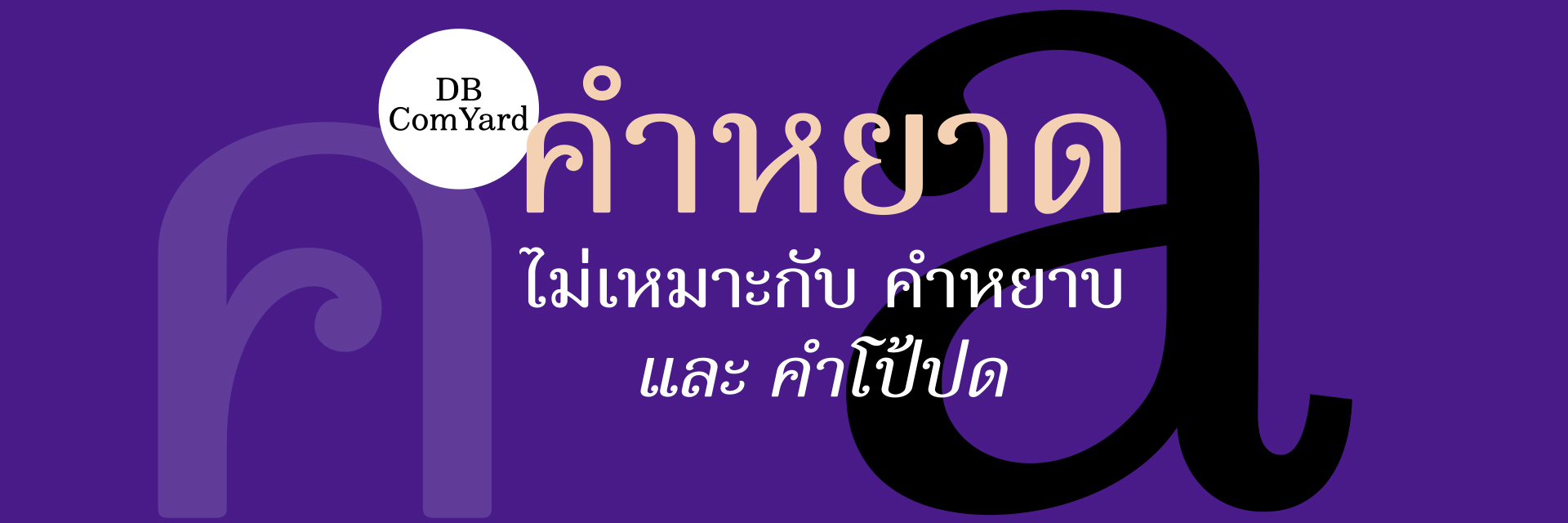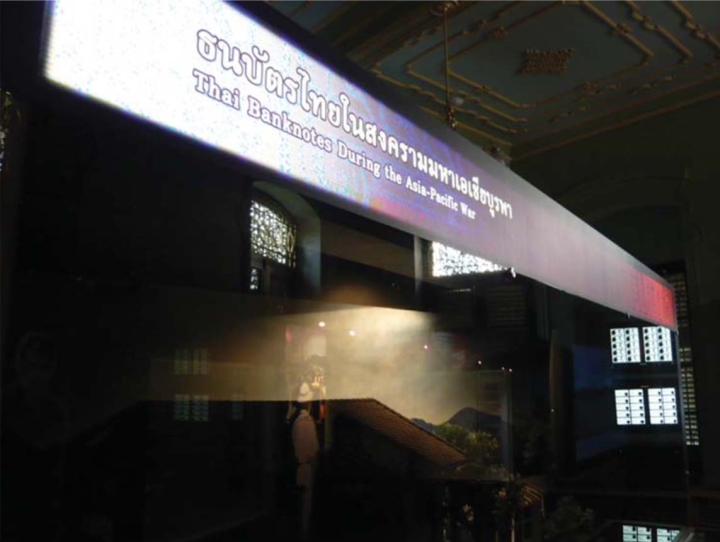
ตัวอักษรประดิษฐ์ของไทยแบบหนึ่ง ซึ่งแม้จะไม่มีหัวกลม แต่ก็ยังสามารถคงลักษณะจารีตประเพณีไว้ได้เป็นอย่างดี, คือ แบบตัวอักษรซึ่งมีหัวเปิด ขมวดปมกลมๆ ที่ส่วนปลายคล้ายยอดอ่อนของใบเฟิร์น, ลักษณะที่ว่านี้สามารถพบเห็นในแบบ ตัวพิมพ์ Clarendon ที่ออกแบบโดย Robert Besley ตั้งแต่ปี ค.ศ.1845 ปรากฏให้เห็นในตัวพิมพ์เล็ก (Lower Case) หลายตัว เรียกว่า "circular terminal". จุดเด่นของตัวอักษรไทยสไตล์นี้อีกประการหนึ่งคือ ส่วนปลายหางอักษรจะมีลักษณะเส้นหนักเบาตวัดปลายคล้าย stroke ที่เกิดจากปลายพู่กันอย่างจีน เราจะเห็นแบบอักษรกลุ่มนี้กระจายอยู่ทั่วประเทศ ตามป้ายร้านค้าเก่าที่ยังอนุรักษ์ไว้, ป้ายโรงเรียน สถานที่ราชการ, วัด, วัง ฯลฯ ด้วยระดับความละเอียดประณีตบรรจงแตกต่างกันออกไปตามระดับฝีมือช่าง, บ้างก็เป็นงานเขียนด้วยสี, บ้างก็เป็นตัวอักษรไม้หรืองานปูนปั้น ฯลฯ
ลักษณะรูปลักษณ์อักษรที่ดูอ่อนช้อยเป็นไทย ดังที่ผมได้กล่าวไปแล้วนั้น เป็นไปได้ว่าเกิดจากการคลี่คลายลายเส้นในงานจิตรกรรมไทยของช่างเขียน ช่างสลัก ช่างปูนปั้นของไทยเอง หรืออาจเป็นการซึมซับปรับปรุงมาจากต่างชาติ (ส่วนหัวมาจากทางยุโรป อเมริกา และส่วนหางมาจากจีน) ก็เป็นไปได้
ถ้าลองย้อนศึกษาดูสิ่งพิมพ์โฆษณาไทยในช่วงปี พ.ศ. 2470-2479 จะพบลักษณะที่ว่านี้ในตัวอักษรที่เขียนด้วยมือเพื่อนําไปทําบล็อคพิมพ์. ตัวเรียงพิมพ์ตะกั่วที่ใช้พิมพ์ในยุคนั้นคงมีเพียงแบบเดียวที่มีลักษณะหัวคล้าย circular terminal คือ "โป้งแซ" ตัวพาดหัวยอดนิยมที่ได้รับการยอมรับว่างดงามที่สุดของยุคตัวเรียงตะกั่ว, อย่างไรก็ตามนับจากโป้งแซเป็นต้นมา ก็ยังไม่มีตัวพิมพ์ยุค phototype setting (ที่คนไทยนิยมเรียกตัวคอมพิว) หรือแม้แต่เป็นแผ่นอักษรลอกที่มีลักษณะหัวอย่างโป้งแซออกมาให้เห็นเลย. เมื่อ PSL Thai Common ฟอนต์ PostScript ของ พัลลภ ทองสุข ออกสู่ตลาดจึงสามารถเติมเต็มช่องว่างที่ขาดไปได้อย่างดี, ลักษณะสําคัญของ PSL Thai Common คือรูปทรงที่ค่อนข้างผอมประหยัดที่ในการใช้พาดหัว, สัดส่วนแบบง่ายๆ คือ รูปอักษรพยัญชนะส่วนใหญ่ที่ดูกว้างใกล้เคียงกัน ประกอบกับรายละเอียดอื่นๆ เช่น เส้นคอของอักษร ค, ต ที่เหยียดตรง ทําให้ชื่อ Thai Common ฟังดูเหมาะสมเพราะรูปลักษณ์ดูเป็นไทยๆ ธรรมดาดี ค่อนไปทาง "ชาวบ้าน" มากกว่า "ชาววัง"
ฟอนต์ไทยกึ่งพาดหัวกึ่งตัวเนื้อ ย้อนยุคกลับไปหาคุณค่าในอดีตด้วยการเพิ่ม "จริต" เข้าไปในรูปอักษร
เพื่อบอกกล่าวอย่างเป็นทางการ เกิดจากการนำ DB ComYard มาปรับปุงส่วนหัว, หาง และสัดส่วนอักษรให้แคบลง
ปัญหามันอยู่ที่ว่า ในโลกยุค Branding ที่ต้องสร้างคุณค่าผ่านตัวพิมพ์นั้น อย่าว่าแต่สินค้าหรือธุรกิจบริการชั้นสูงที่เน้นความเป็นไทยเลย แม้แต่ร้านอาหารไทยเล็กๆ หรือสินค้า SMEs ที่อยากดูดีกว่า OTOP แบบพื้นๆ ก็ยังมีความต้องการยกระดับภาพลักษณ์เช่นเดียวกัน, PSL Thai Common ซึ่งตั้งใจเกิดมาเป็นชาวบ้านจึงไม่อาจรองรับความต้องการได้ครบ. ยิ่งถ้าเป็นงานที่ใช้สื่อถึงงานศิลปะชั้นสูง หรือถวายงานเจ้านายชั้นสูงแล้ว ตัวพิมพ์ยิ่งต้องเพิ่มความประณีตวิจิตรบรรจงเข้าไป เพื่อให้ได้บุคลิกสอดคล้องกับเรื่องราวที่นําเสนอ. กล่าวอย่างเป็นธรรม ไม่มีแบบฟอนต์ใดในโลกที่ใช้ได้ครอบจักรวาล, ดีบี คําหยาด จึงถือกําเนิดขึ้นเพื่อเป็นการช่วยเติมเต็มช่องว่างที่ขาดหายไปให้สมบูรณ์ยิ่งขึ้นไปอีก
การกําหนดสัดส่วนโดยรวมของตัวพิมพ์ "คําหยาด" ชุดนี้ ผมตั้งเป้าให้ใกล้เคียงกับแบบตัวพิมพ์เนื้อความมาตรฐานของไทยให้มากที่สุด ทั้งนี้เพื่อให้สามารถใช้เป็นตัวหัวข้อรอง (subhead) หรือตัวโปรยให้อ่านยาวๆ ได้ง่าย โดยไม่ต้องนํา PSL Thai Common มาสั่งเพิ่มความกว้างเหมือนที่เคยนิยมทํากันมา) หรือแม้แต่ใช้พิมพ์ร่วมเป็นส่วนหนึ่งในเนื้อความได้โดยที่ยังดูกลมกลืนไม่แปลกแยกจากกัน. รายละเอียดส่วนใหญ่ในเส้นร่างของผมเป็นการประสมเล็กประสมน้อย จากสิ่งประทับใจที่ซึมซับมาจากงานโฆษณาเก่าๆ, จากป้ายห้างร้าน, สถานที่ ราชการ, วัดวาอาราม ฯลฯ ส่วนที่ถูกให้ความสําคัญเป็นพิเศษ คือส่วนหางที่มีลักษณะตวัดปลายซึ่งถือว่ายากที่สุด (ต้องหยาดเยิ้มสมกับชื่อที่ตั้งไว้ในใจ). นอกจากนั้นยังให้ความพิถีพิถันกับการถ่ายน้ําหนักของตัว ร, โ, ใ, ไ ไม่ให้ดูเทล้มไปข้างหน้า เพื่อให้ทุกถ้อยคําที่ถูกถ่ายทอดด้วยตัวพิมพ์ชุดนี้ นอกจากจะฟังดูระรื่นหูแล้ว ยังน่าเชื่อถือไม่โยกโย้กลับไปกลับมา ถ้าเอาไปทําตราสินค้า ทําบรรจุภัณฑ์หรือโฆษณา นอกจากจะดูระรื่นตาแล้ว ยังสามารถบ่งบอกถึงระดับมาตรฐานคุณภาพของสินค้าและบริการ
ห้องธนบัตรไทย
โดยบริษัท แปลน โมทิฟ จำกัด
ใช้ฟอนต์ DB ComYard เป็นตัวพาดหัว
โดย เอนก นาวิกมูล แสดงถึงการใช้งานร่วมกันระหว่างตัวอักษรฝีมือช่างบล๊อค (ห้างขายยาตรานกยูง) และตัวเรียงตะกั่ว "โป้งแซ" (โอสถสตรี) ที่มีลักษณะหัวคล้าย circular terminal ในแบบตัวพิมพ์ Clarendon
ถ้าลองมองเงยหน้าดูป้ายบอกทางของกรมทางหลวงหรือ การทางพิเศษฯ จะพบว่าแบบตัวอักษรดูธรรมดาและเรียบง่าย กว่าทั้ง PSL Thai Common และ ดีบี คําหยาด เนื่องจากหัวอักษรเป็นจุดกลมทึบและหางเรียวแหลมเป็นส่วนใหญ่, ผมจึงปรับปรุง ดีบี คําหยาด เป็น ดีบี คําบอก โดยการ "ลดจริต" ให้ดูคล้ายตัวป้ายบอกทางเพื่อเป็นทางเลือกให้นักออกแบบใช้ทําภาพเลียนแบบป้ายในงานโฆษณา หรือใช้พาดหัวเพื่อบอกเล่ากล่าวเตือนที่ดูเป็นทางการ (มากกว่า PSL ThaiCommon หรือ ดีบี คําหยาค ซึ่งค่อนไปทางจารีตประเพณี, ศิลปะวัฒนธรรม)
ชื่อ "คําหยาด" ผมตั้งตามชื่อหนังสือกวีเล่มโปรดที่เขียน โดยอาจารย์เนาวรัตน์ พงษ์ไพบูลย์, ดีบี คําหยาด และ ดีบี คําบอก สะกดด้วยอักษรโรมันเป็น DB ComYard และ DB ComBork ตามลําดับ และที่สะกดด้วย 'Com' แทนที่จะเป็น 'Cum นั้นไม่ ได้ตั้งใจให้ดูคล้าย PSL Thai Common แต่อย่างไร
คําว่า 'Cum" แปลว่า "อสุจิ ถึงไม่หยาบก็ควรเลี่ยงเป็น "Com" แทนครับ !